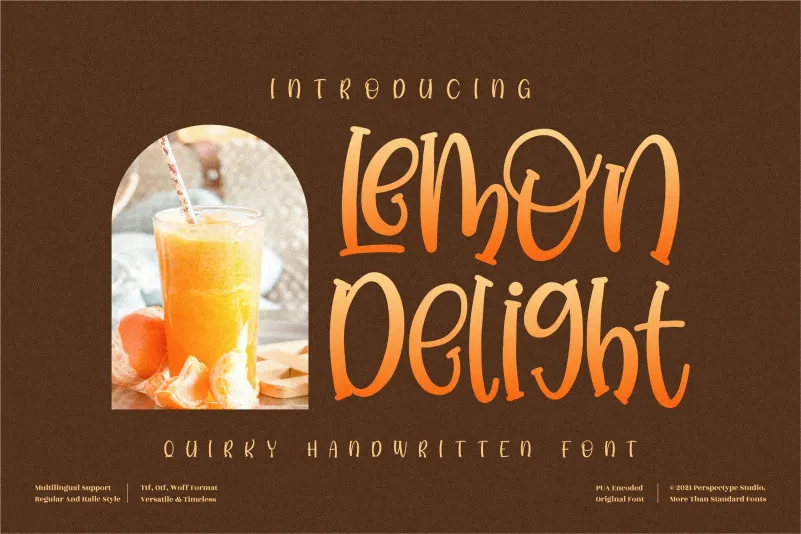
Lemon Delight Font – Download Grátis
Esta é uma fonte escrita a mão com um toque peculiar e natural. Ela se destaca para diversos projetos de design, especialmente aqueles que precisam de um toque casual e amigável. Virem-se apaixonados por sua versatilidade impressionante e use-a para criar designs incríveis! Se você é fã de personalidades divertidas e inovadoras, certamente vai gostar desta fonte. É perfeita para aqueles momentos em que queremos algo um pouco diferente no nosso design. Seja para anúncios publicitários, camisetas, cartões de visita ou até mesmo gráficos de redes sociais, a ‘Lemon Delight Font’ certamente encaixa-se como uma luva. Não espere mais, invista em sua criação e veja o potencial desta fonte para deixar seus trabalhos ainda mais singulares!